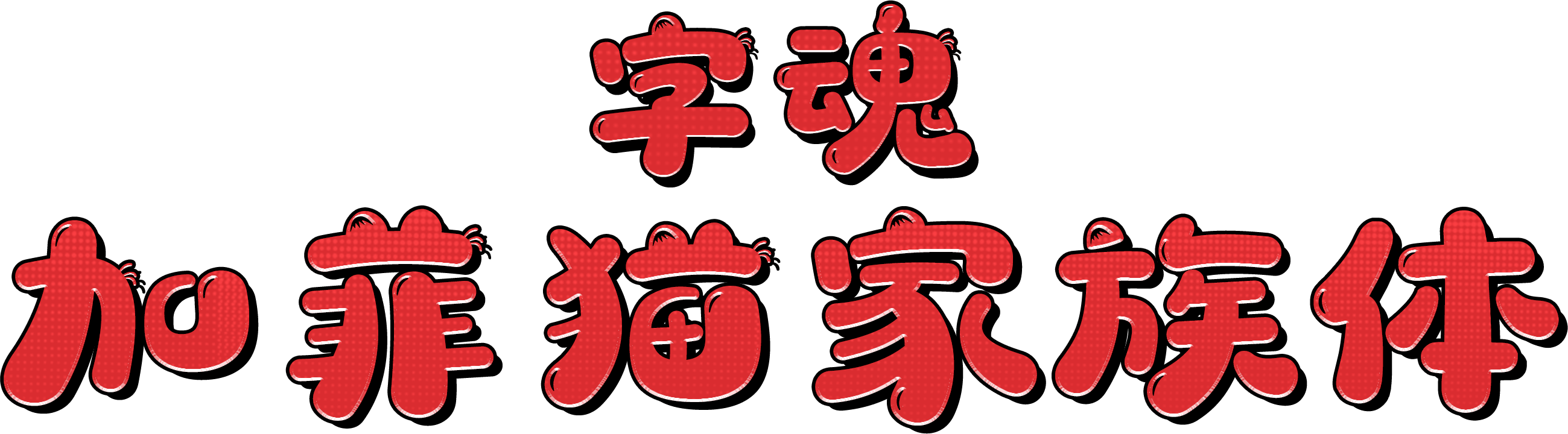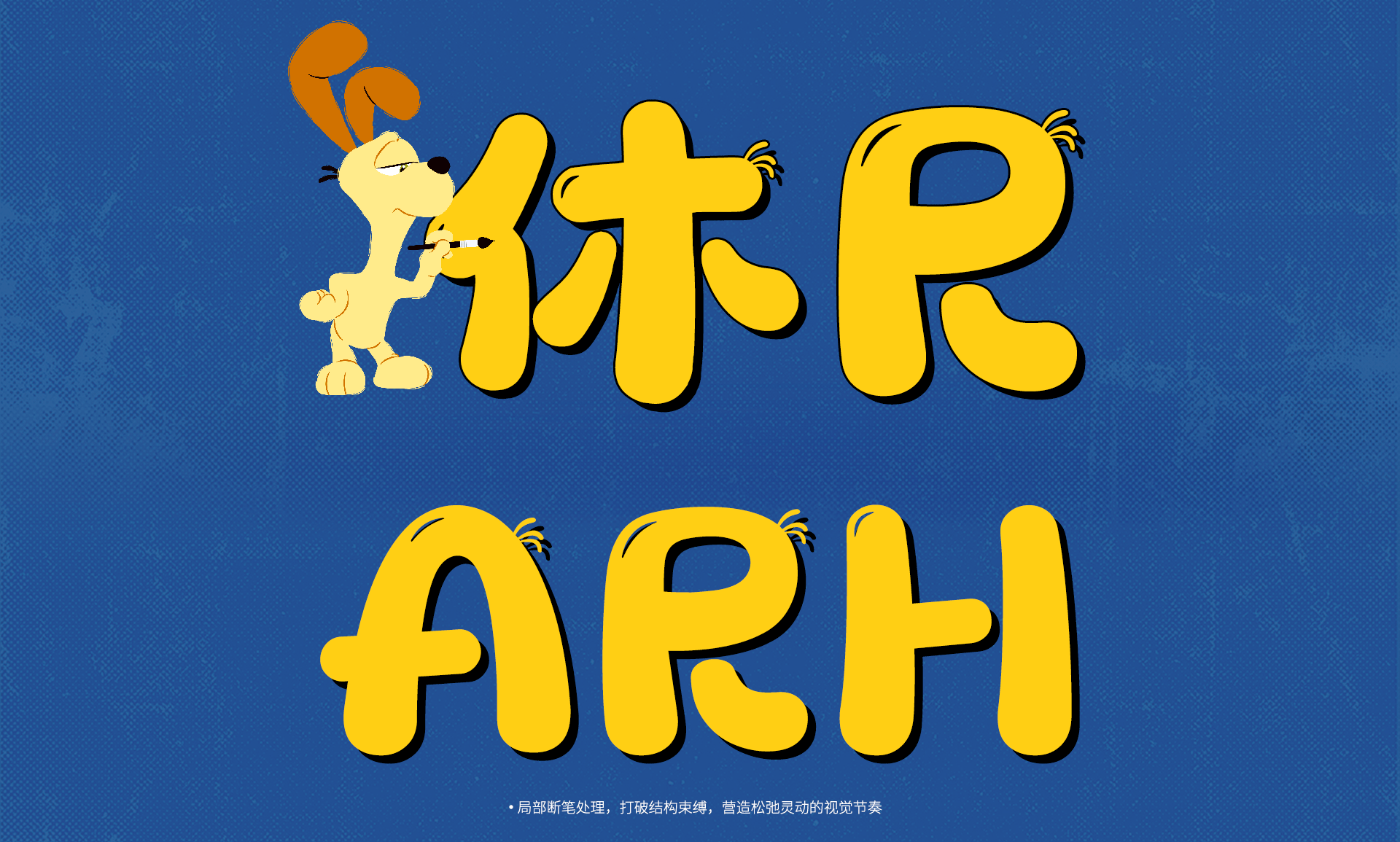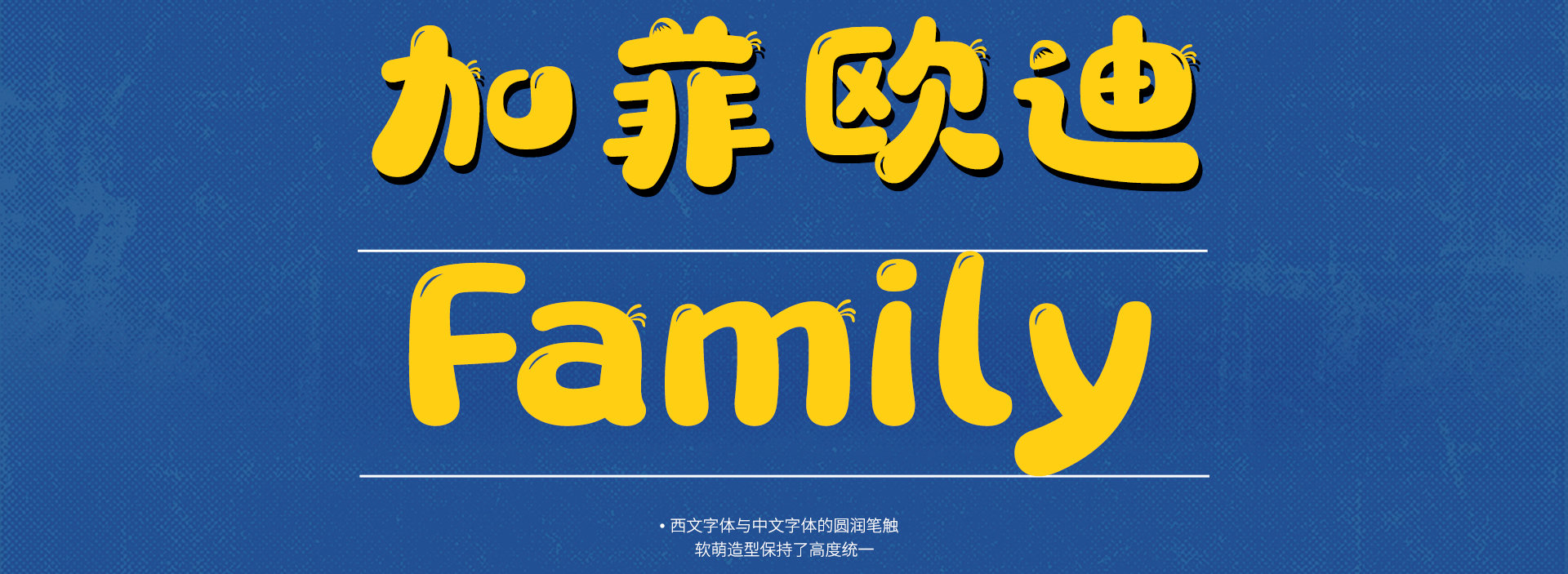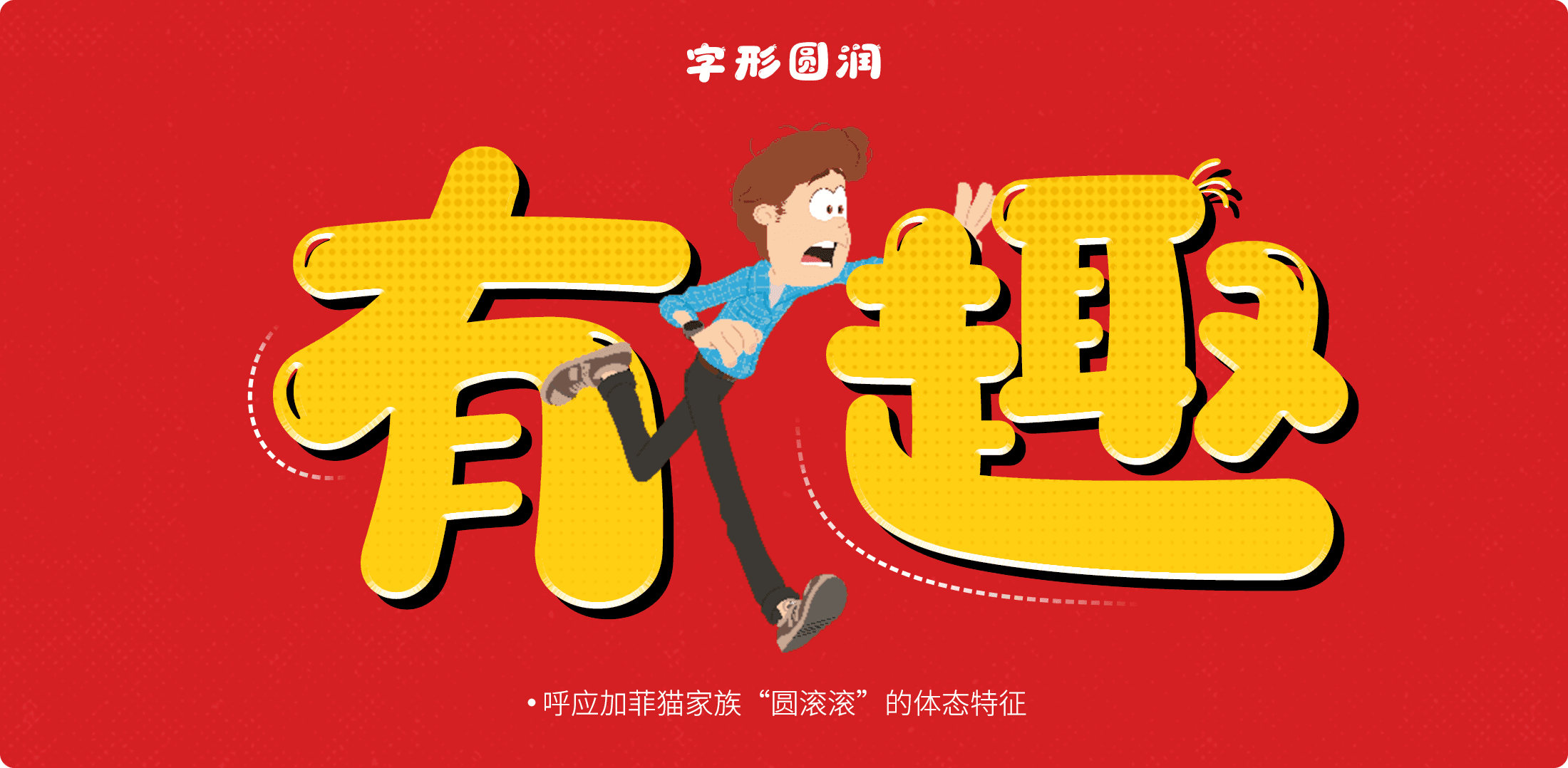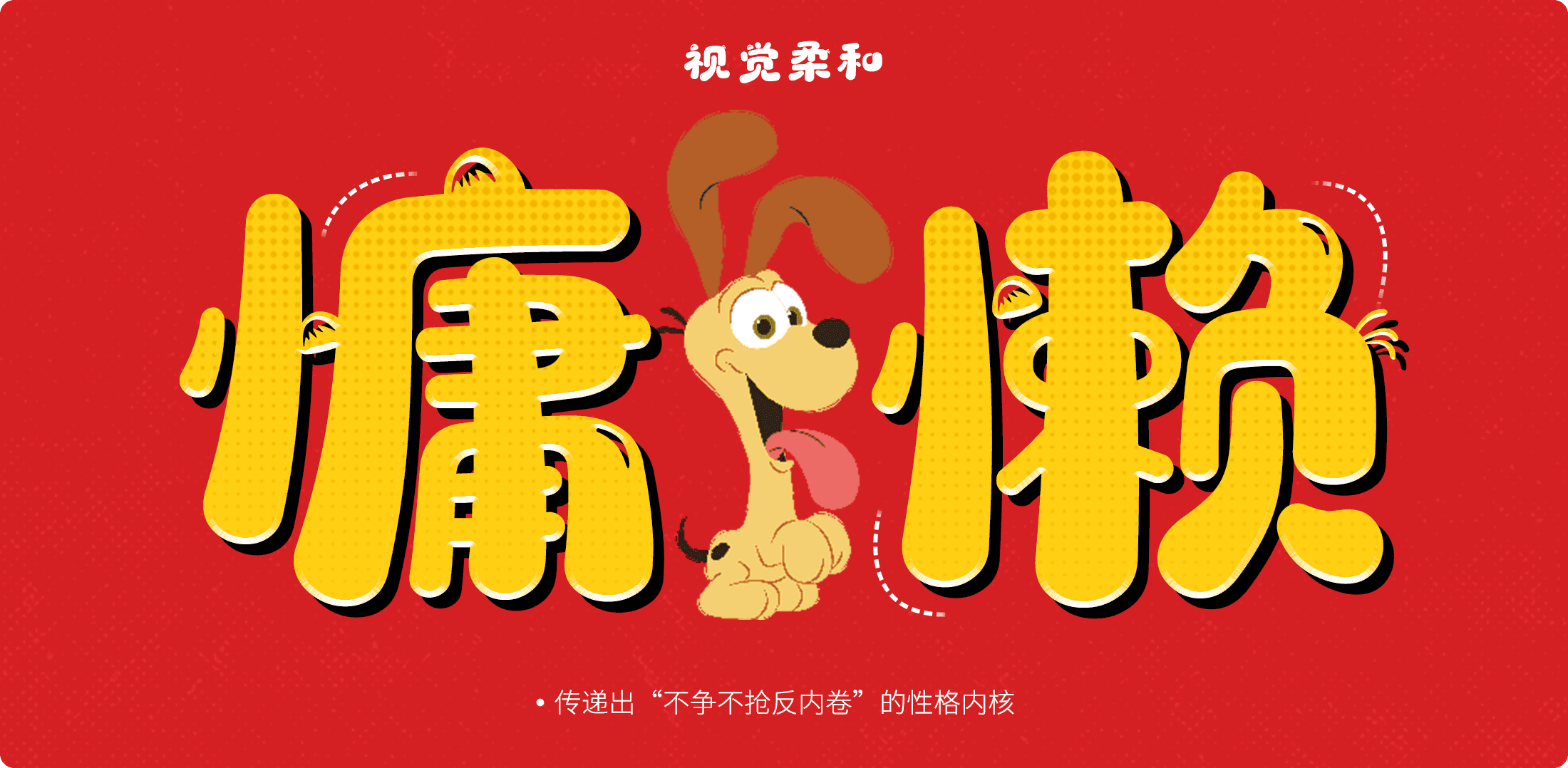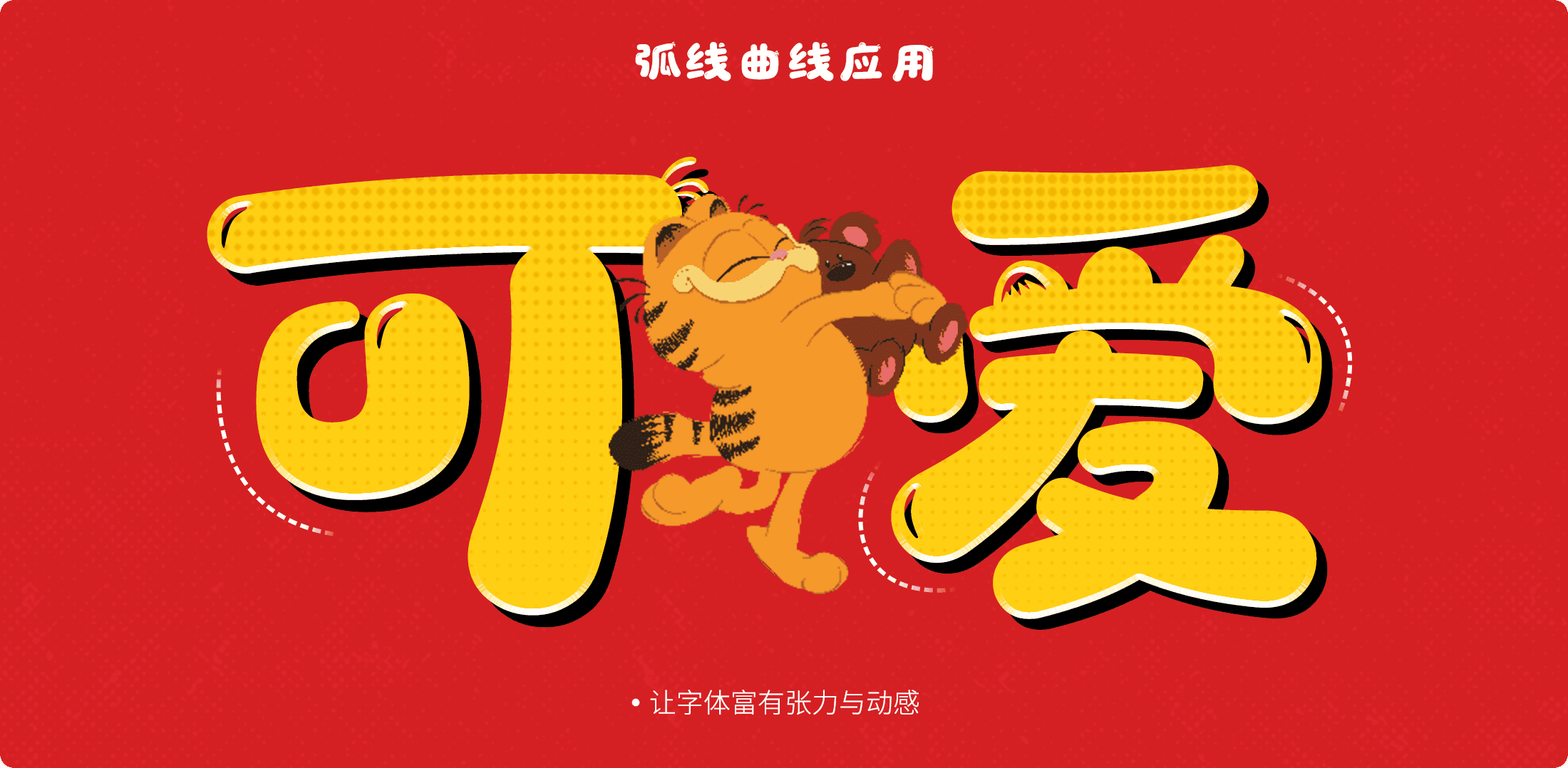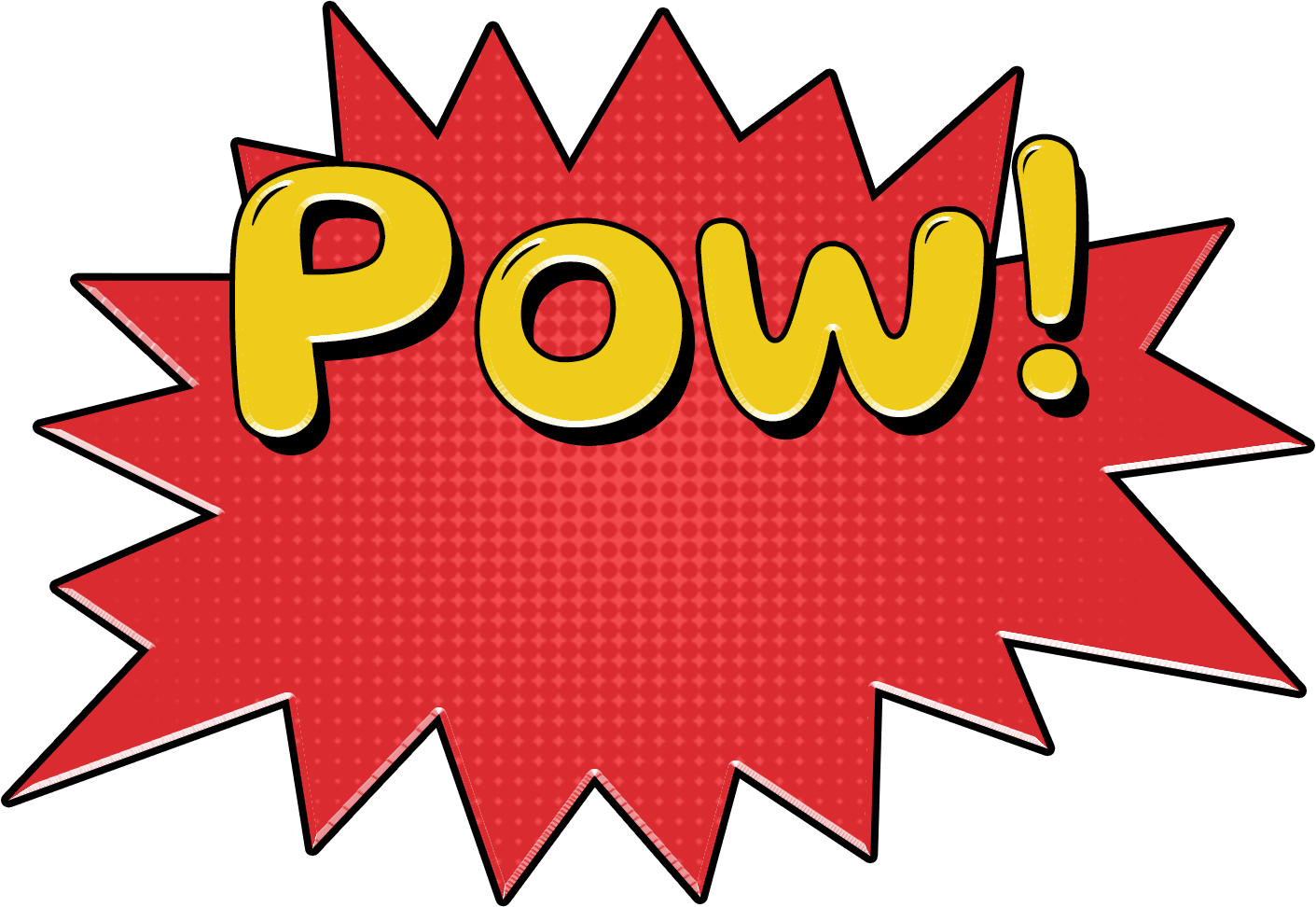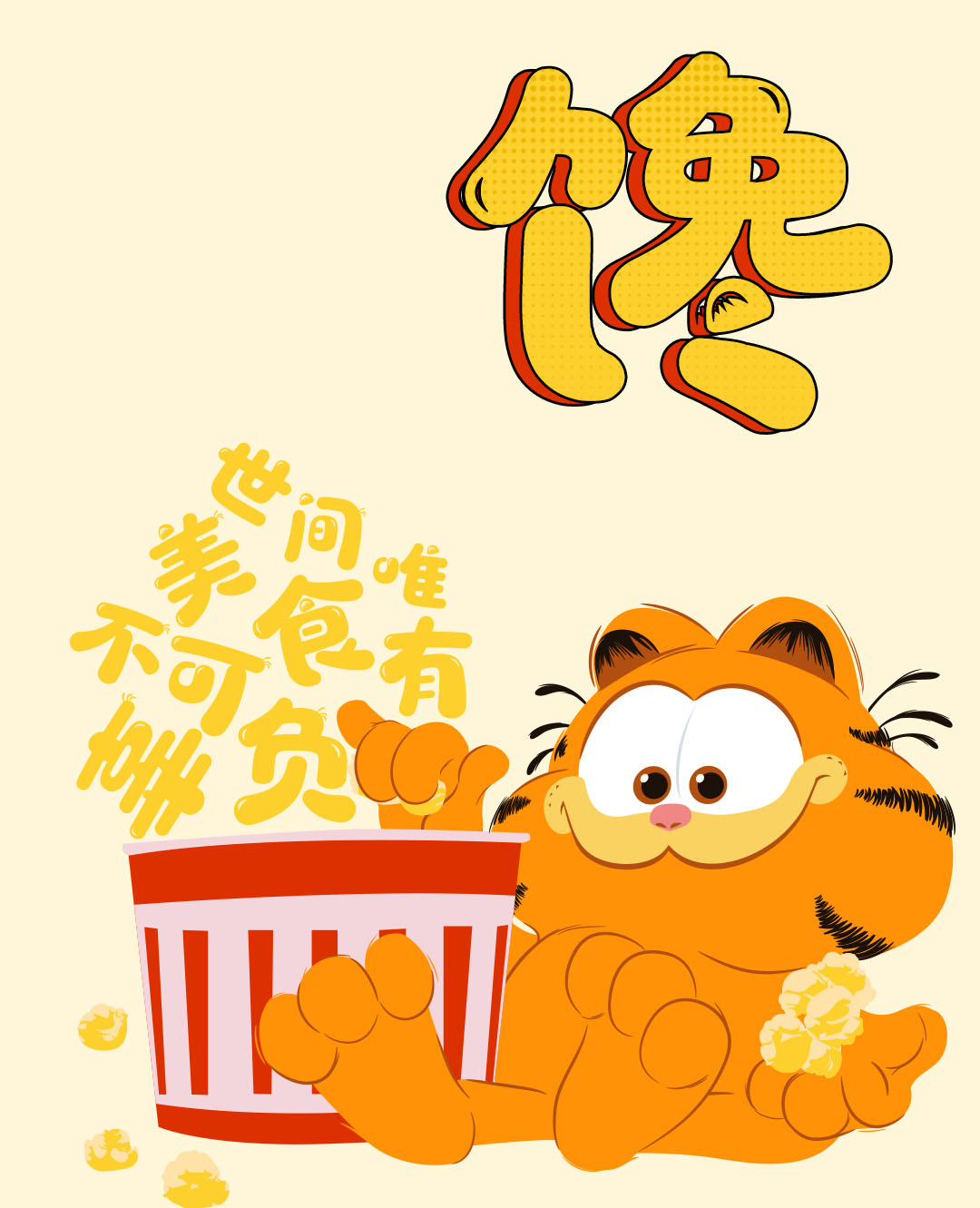
字魂加菲猫家族体字魂和加菲猫授权标识萌趣登场 自在治愈欧迪加菲猫
字魂为全球经典IP加菲猫家族打造的定制字体重磅上线
以字体塑造 IP专属视觉符号
转译经典形象打造专属特色通过对卡通形象的深入分析,设计团队总结提炼出3组图形,将加菲猫家族高度辨识的形象特征融入笔画设计加菲猫字体视觉符号动效
圆润质感强化独有气质加菲猫家族凭借慵懒治愈风格收获广泛好感
高光效果突出视觉立体感高光效果的加入为字体增加了立体和层次感猫咪高光效果动效
中西文匹配面向加菲猫家族全球化的品牌布局加菲欧迪 Family 字体动效ARH 字体动效
小写字母融入手写灵动笔触,笔画富有弹性,突出活泼俏皮气质
字魂加菲猫家族体能够全面适配加菲猫家族 IP 全商业生态与宣发场景